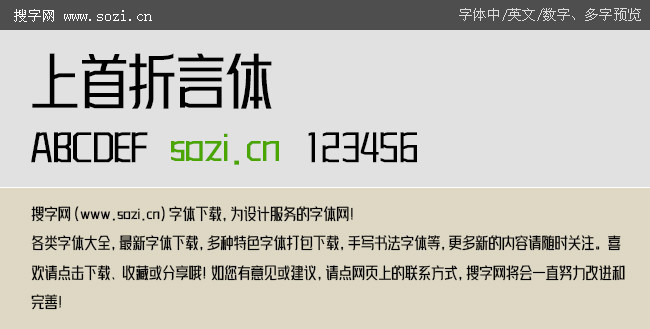
上首折言體
搜字網(wǎng)給大家提供一款上首新藝體中文字體下載,上首折言體字形沉穩(wěn)又富有張力,表現(xiàn)出穩(wěn)重而又不失個性。橫豎筆剛直,撇捺柔化,剛柔共存,展現(xiàn)出非凡的特性,文字較為高瘦,展現(xiàn)出獨有的氣質(zhì)。適用于搭配標志、廣告標語、商業(yè)廣告等廣告設計。